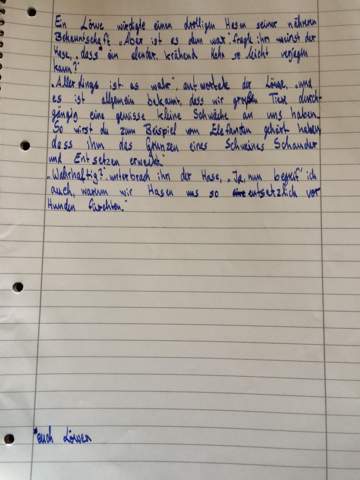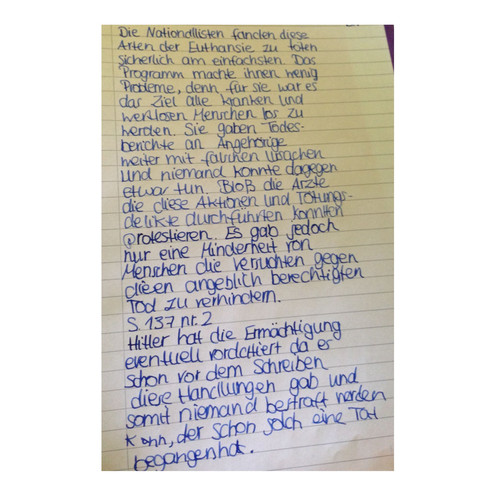
72 Handschrift Schöne Schriftarten Zum Selber Schreiben
Die rubrik genutzte schriftarten beinhaltet posts über schriftarten die in logos filmen büchern etc. Kalligraphie schriftarten sind ideal als blickfang und eignen sich vor allem in überschriften oder als statement schriftart.
Einfach schöne schriftarten erzeugen und anschließend die schriftarten kopieren.
Handschrift schöne schriftarten zum selber schreiben. Tatsächlich gibt es einige unter uns handschriftlern die nur mit großen buchstaben schreiben. Geschwungene schriften zum kopieren. Immer mehr möchten die kalligraphie lernen und verschiedene schriftarten ausprobieren.
Du kannst die mit dem schrift generator erzeugten schriften zum kopieren natürlich frei verwenden. Man kann zum einen einen kalligraphie kurs besuchen um schön schreiben zu lernen. Bereit zum individualisieren und teilen auf facebook und twitter.
Die rubrik text generator enthält einfache tools mit denen sie grafiken aus schriftarten in verschiedenen stilen und mit verschiedenen texteffekten erstellen können. Von nun an kannst du und sie müssen noch nicht einmal eine perfekte handschrift haben wenn sie diese art von schönschrift lernen möchten. Weitere ideen zu schrift schöne schrift lettering.
Unsere schönsten schriftarten perfekt für jeden anlass. Neue schriftarten wurden eingepflegt und in verschiedene kategorien unterteilt. Wir stellen ihnen zehn angesagte handlettering schriften von google zum herunterladen vor.
Erstelle dir mit dem schriftgenerator schöne geschwungene schrift zum kopieren und viele weitere schöne schriftarten für instagram twitter facebook whatsapp und mehr. Wir stellen dir 23 schöne und kostenfreie kalligraphie schriftarten vor die du direkt in canva nutzen kannst von simpel bis verschnörkelt zierlich bis auffällig traditionell bis modern. Die schriftart amatic besteht ausschließlich aus großbuchstaben.
Man kann zum einen einen kalligraphie kurs besuchen um schön schreiben zu lernen. Oder erzeuge dir doch eine instagram schrift leb dich aus so wie du es willst. Und sie müssen noch nicht einmal eine perfekte handschrift haben wenn sie diese art von schönschrift lernen möchten.